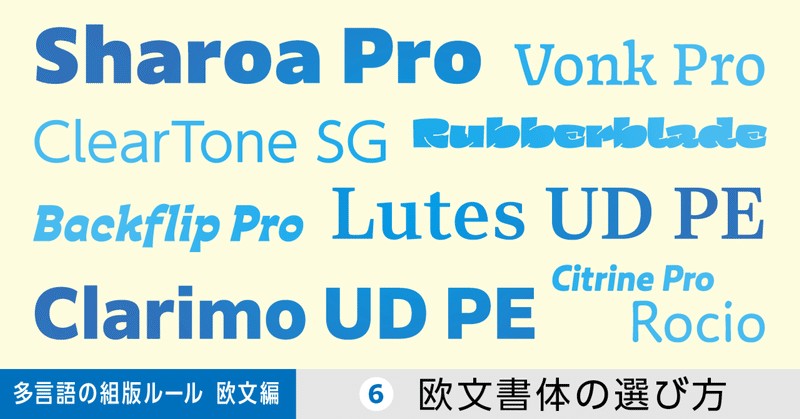
多言語の組版ルール【欧文編】第6回 欧文書体の選び方
今回でいよいよ【欧文編】は最終回。
上質な欧文組版を目指すには、どのようなフォントを選んで組むと良いのでしょうか。連載中に紹介してきた基礎知識を振り返りつつ、書体選定のコツをお伝えします。
1. 本文組みの書体を選ぶとき
欧文組版に使う書体を選ぶ場合、数行程度のキャッチコピーや見出し用であれば、文字のデザインだけを優先して選んでも、手動で文字/単語間隔を調整すれば問題はないでしょう。
しかし、本文組みの場合、効率的なオペレーションを考慮する必要があるため、これから組もうとしているテキストがどのようなものなのかを把握して選択する必要があります。
たとえば、イタリック体を使うべき箇所があるなら、ローマン体のほかにイタリック体が用意されている書体を選ばなくてはいけません。
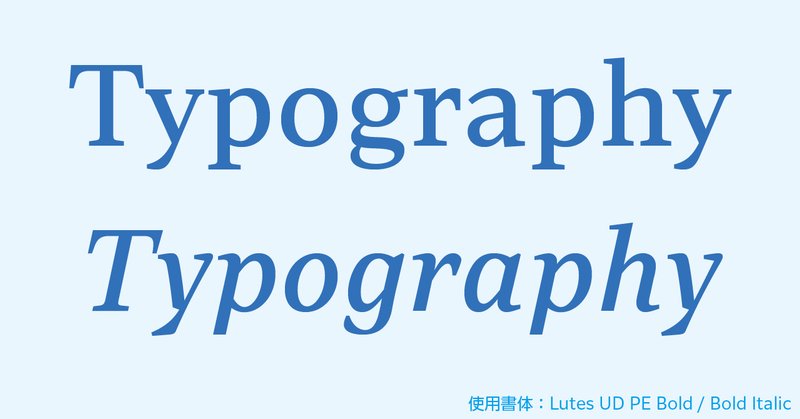
また、英語以外の言語で、その言語特有のアクセント記号付き文字が必要な場合は、その文字を含む書体が必要です。
例えば「浅草寺」という言葉を「Senso-ji」ではなく「Sensō-ji」と表記するルールなら「ō」のグリフ(マクロン)がない書体では正しく組むことができません。
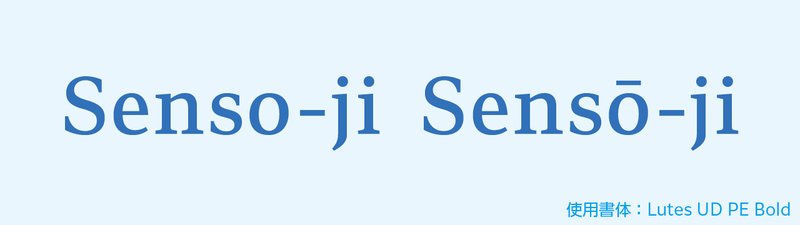
フォントによって、合字(リガチャ)やアクセント記号(ダイアクリティカルマーク)付き文字、分数などのグリフの有無も異なります。組むテキストに足る文字があるか、確認をしましょう。
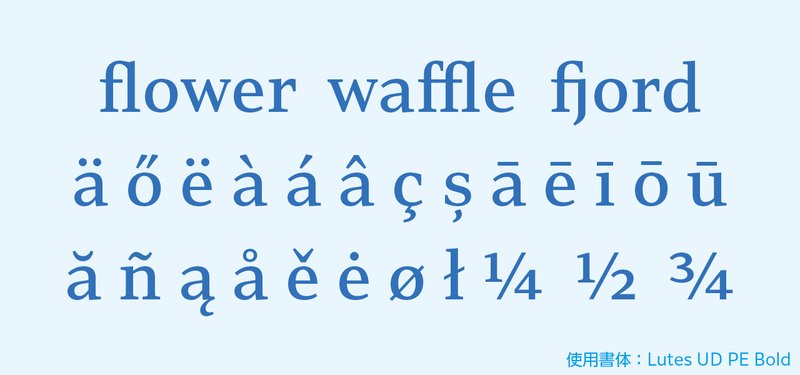
強調などのために文字を太くする処理が考えられる場合は、太いウエイトが用意されているか、確認が必要です。
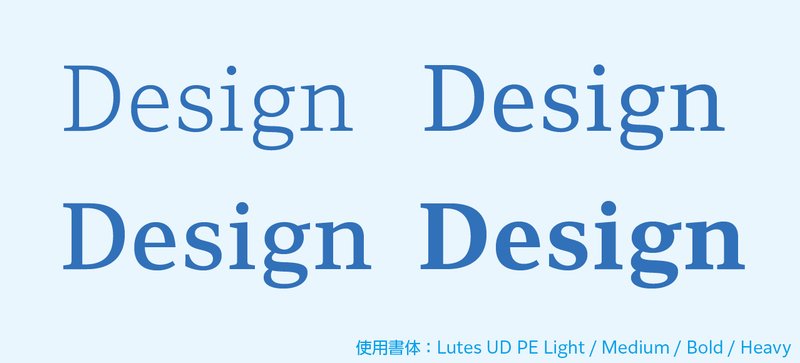
ウエイトバリエーションが豊富な書体であれば、本文から見出しまで同一のファミリーで組むことができます。
2. 質のよい書体を選ぶには
これらの条件を満たしているうえで、さらに大切な選定条件は、その書体が「質のよい書体」であるかどうかです。
確認するためには、実際にテキストを流し込んでみて、レタースペースにおかしなところがないか見てみます。
どこを見ればよいかわからない場合は、以下の単語を試してみましょう。
レタースペースが確認しやすい単語
①「LA」「To」「Tr」「Ta」「Tu」「Te」「Ty」「Wa」「We」「Wo」「Ya」「Yo」を含む単語
②「P.M.」「AWAY」などの大文字だけの単語
レタースペースが不自然な場合、本文に使うべきかどうかを慎重に検討する必要があります。
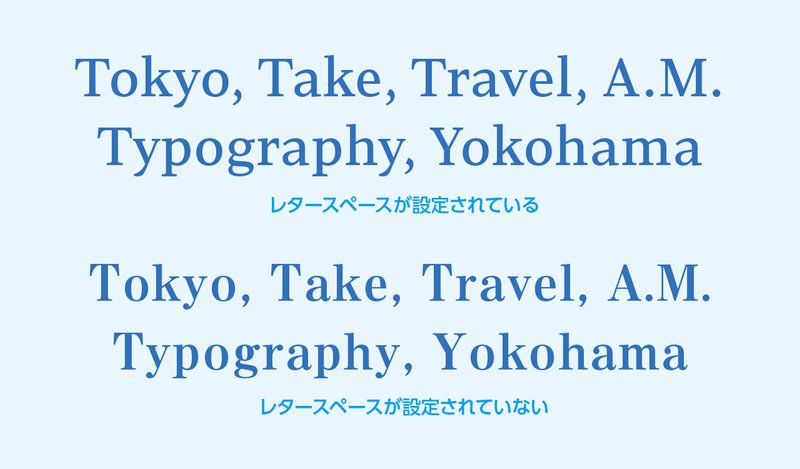
欧文書体には個性的な新しいデザインの書体、世界中で永く愛されている書体など数多くの選択肢がありますが、上記のポイントを押さえて、組む内容に適した書体を見分けましょう。
【参考】MORISAWA PASSPORTで使える欧文書体
1. Lutes UD PE
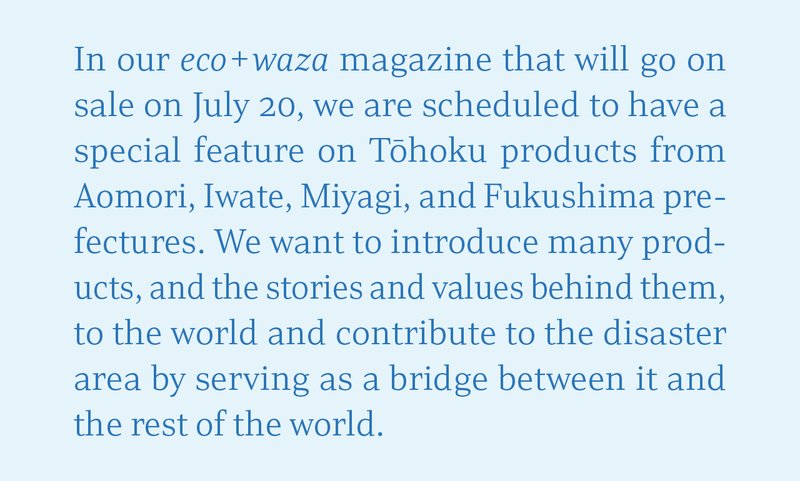
「Lutes UD PE」は、デジタルデバイス上での視認性に配慮した、すっきりとした印象のセリフ書体です。
ラテンアルファベットに加えてキリル文字、ギリシャ文字、ベトナム語用文字を カバーする「PE」(汎ヨーロッパ)の文字セットで、151もの言語に対応。
和文をはじめ中文、韓文も揃うモリサワのUD黎ミンシリーズと併用しやすいデザインです。
2. Clarimo UD PE
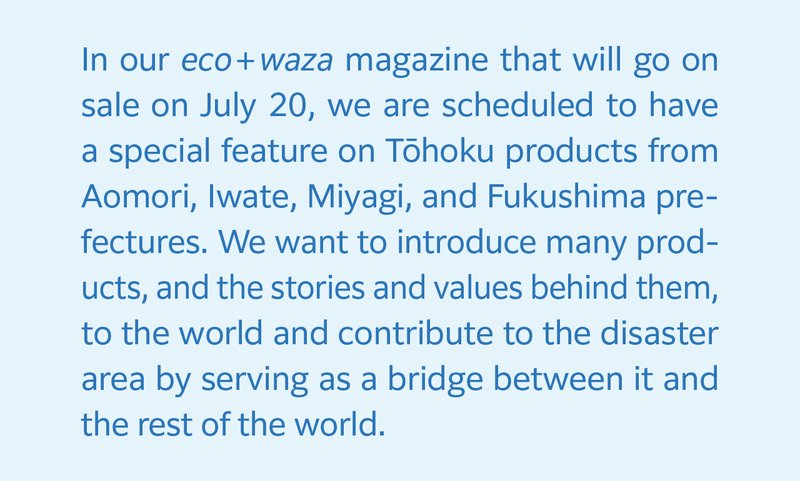
「Clarimo UD PE」は、上のLutes UD PEと同じく「PE」(汎ヨーロッパ)の文字セットを採用しているサンセリフ書体。
ExtraLightからUltraまで8ウエイトを揃えており、本文はもちろん広告や標識表示など、さまざまな媒体・シーンに使えます。
3. Sharoa Pro
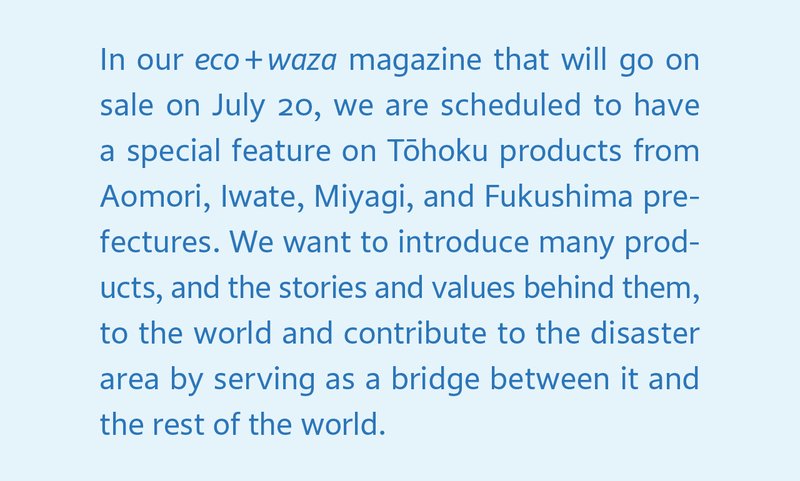
「Sharoa Pro」は、明快なエレメント、やや広めのカウンターで読みやすい欧文書体として2021年にリリースしました。骨格には手書きの風合いが残されており、温かな印象を与えるヒューマニストサンセリフ書体としての特徴を備えています。
10ウエイト展開と、スモールキャップや数字のバリエーションが豊富に搭載され、本格的な本文組みに対応した書体です。
4. Backflip Pro
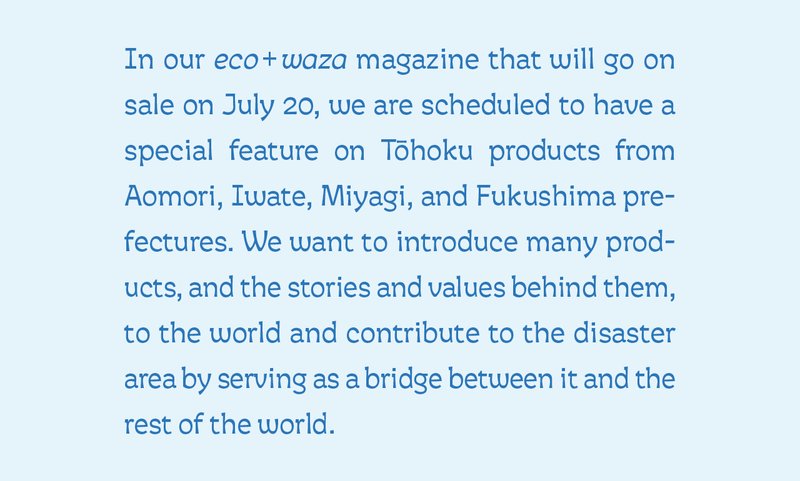
「Backflip Pro」は、軽快で遊び心のあるディスプレイ書体です。
細いウエイトはオーガニックで優しい雰囲気を醸し出します。また太いウエイトでは、フレア(末広がりな始筆や終筆の先端の形状)や、一般的な書体とは反対のコントラスト(抑揚)が強調されることで、ユニークで独創的な表情を演出します。製品パッケージや広告コピーなどの利用はもちろん、短めの本文組みでも読みやすさを発揮できます。
5. Vonk Pro
「Vonk Pro」は、モリサワタイプデザインコンペティション2016欧文部門でモリサワ賞金賞・明石賞を同時受賞した、現代的な本文用セリフ書体です。
カリグラフィックな骨格に柔らかさと鋭さが混在するユニークなエレメントを採用しており、オリジナリティ溢れるデザインです。抑揚をおさえて丁寧なカウンターの設計を行っているため、小さな文字サイズや低解像度のディスプレイ環境でも本文書体としての見やすさを失わない点が特徴になっています。
6. Citrine Pro
「Citrine Pro」は、20世紀初頭の活字から影響を受けたサンセリフで、明るく幾何学的な要素を取り入れつつも、レトロで優しい風合いをもつヒューマニストサンセリフを目指して作成されました。
A1ゴシックとの和欧併記を目的に作られ、墨だまりや角丸処理といった共通のエレメントを採用しています。